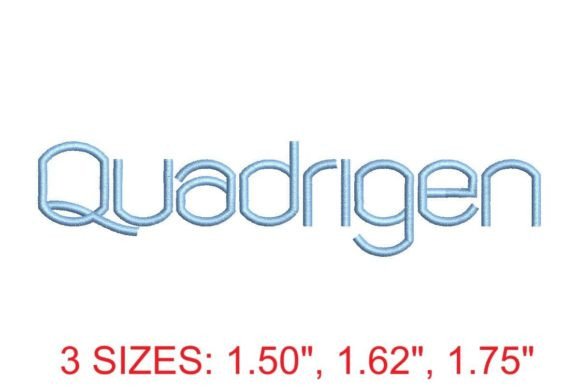
Quadrigen Embroidery Font
Jika anda sedang mencari aset berkualiti tinggi seperti Quadrigen Embroidery Font, pakej premium ini merupakan pilihan yang hebat untuk projek kreatif anda.
Dicipta dengan ketepatan, Quadrigen Embroidery Font menyediakan vektor yang bersih, tipografi yang licin dan lesen komersial untuk ketenangan fikiran.
Sama ada anda mencipta produk POD (Print on Demand), jemputan perkahwinan atau grafik media sosial, Quadrigen Embroidery Font amat bersesuaian.